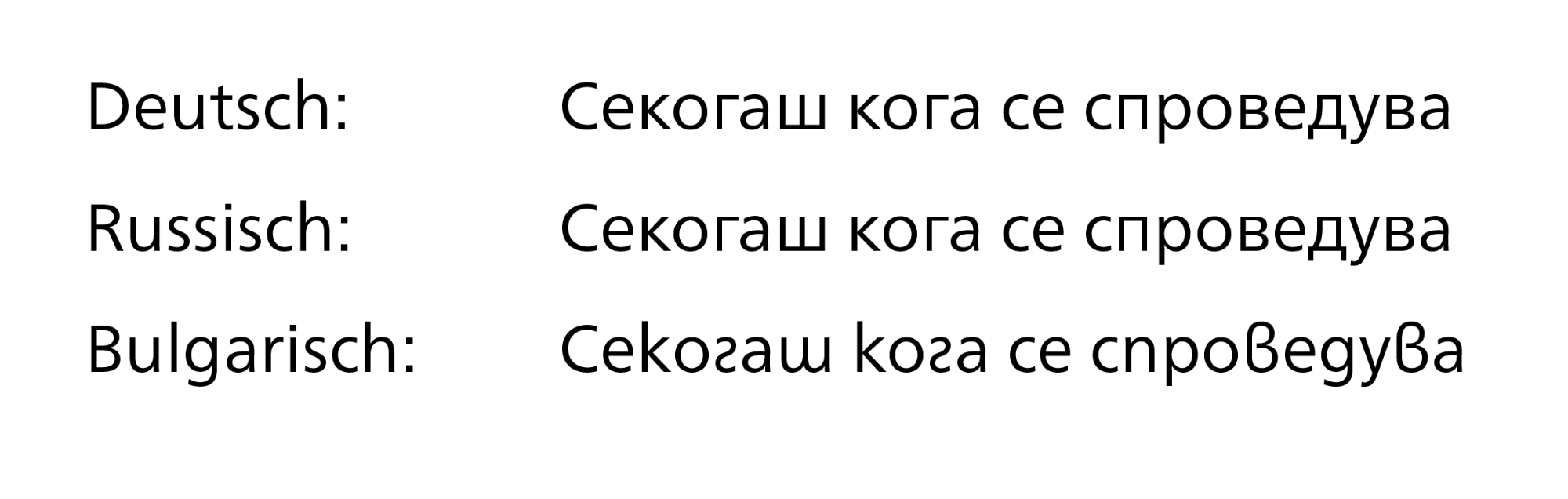
Neue Frutiger World -> Kyrillisch variiert je nach Spracheinstellung
Ich sitze gerade an einer Broschüre in Mazedonisch. Dafür hält InDesign leider keine Spracheinstellungen bereit und die Sprache die am nächsten kommt ist Bulgarisch. Stelle ich bei der Neuen Frutiger World »Bulgarisch« als Sprache ein ändern sich etlichen Glyphen im Text und diese haben, soweit ich das per Wikipedia nachvollziehen kann, nichts mit Bulgarisch zu tun. Mit den Einstellungen für »Deutsch« oder »Russisch« sieht alles aus wie es soll – nur leider funktioniert dann die Silbentrennung nicht. Wechsle ich auf die Tahoma wird auch »Bulgarisch« wie es soll dargestellt. Hat jemand eine Idee woran das liegen könnte und wie ich das fixe?
Hat jemand eine Idee woran das liegen könnte und wie ich das fixe?
Hast Du ein Stylistic Set am Start? Die Glyphen bei Bulgarisch sehen aus wie alternative Zeichen, sofern ich Russisch als Maßstab nehmen kann. Das /g/, /b/, /d/ /p/ bei Bulgarisch kenne ich im Russischen als handschriftliche bzw. kursive Variationen der Glyphen, wie sie bei Russisch zu sehen sind.
Am Besten fragst Du die Auftraggebenden, welche Variante diese bevorzugen, da das bulgarische Kyrillisch sich vom mazedonischen und dieses vom russischen unterscheidet bzw. unterscheiden kann: https://de.wikipedia.org/wiki/Kyrillisches_Alphabet#Kursive_und_aufrechte_Formen
In dem Absatz gibt es auch die Aussage, dass einige Fonts automatisch die landesspezifische Glyphenvariante abhängig von der Dokumentensprache darstellt.
soweit ich das per Wikipedia nachvollziehen kann, nichts mit Bulgarisch zu tun
Doch doch, das sind die ausdrücklichen, sprachspezifischen Alternativzeichen für Bulgarisch.
In traditional Bulgarian typesetting, the upright shapes of characters д (d), г (g), и (i), п (p), т (t) and ш (sh) resemble their cursive forms, i.e. they look similar to Roman lowercase letters g, ƨ (mirrored s), n and m, respectively, instead of like small capital letters as in Russian.
Jetzt bleibt noch die Frage ob diese Formen auch in Mazedonisch üblich sind und ich fürchte fast dass sind sie nicht.